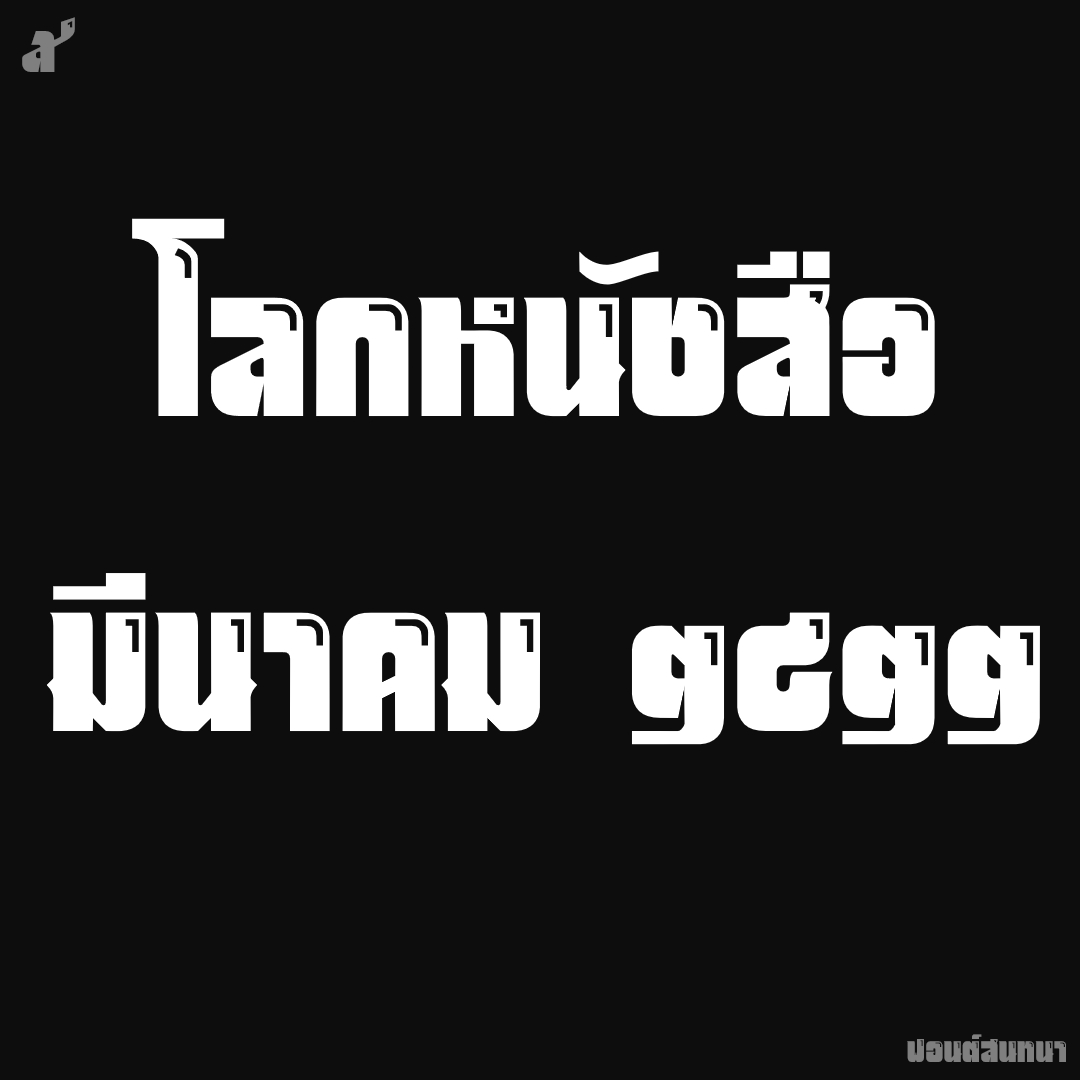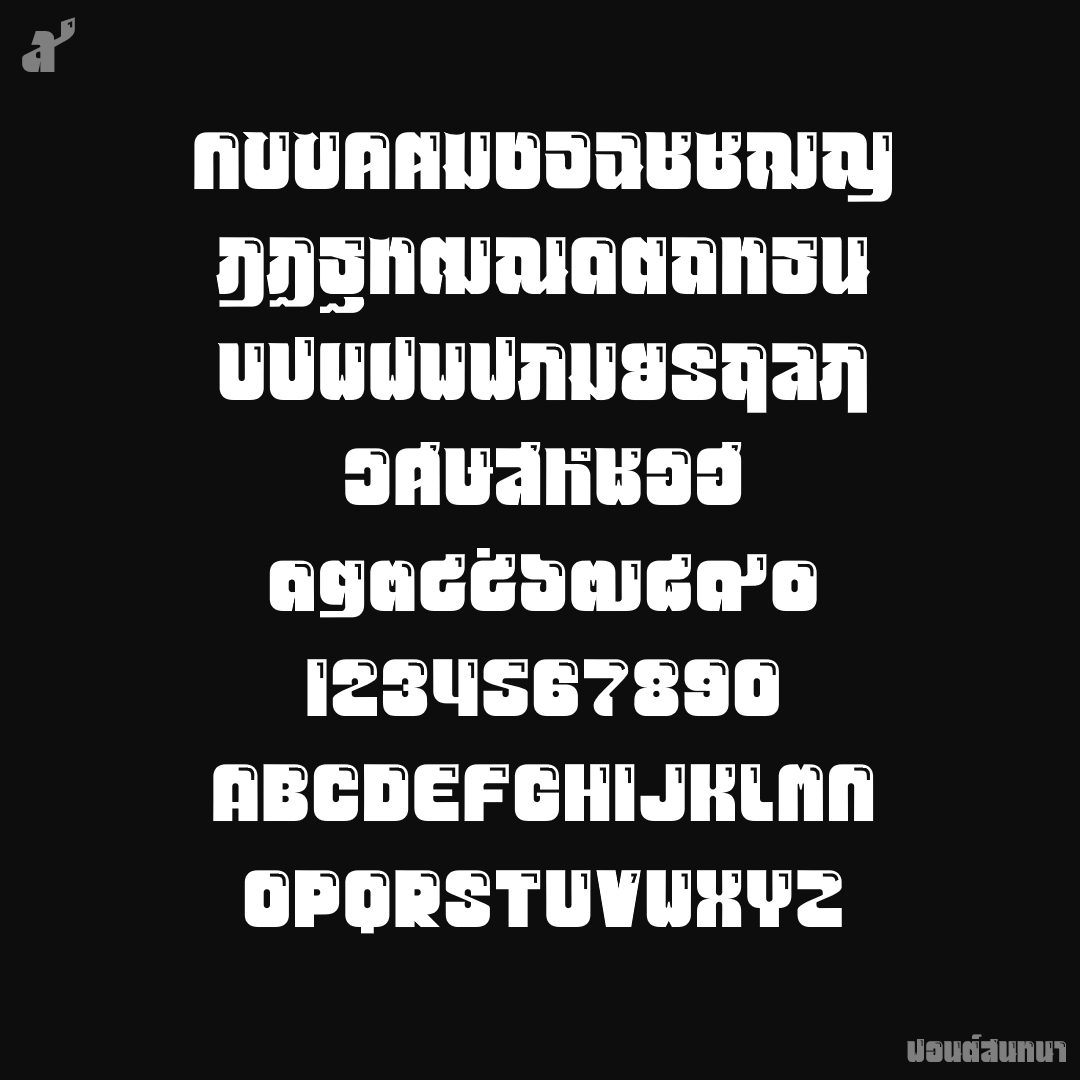
ฟอนต์ สนทนา
ต้นทางจากโลกหนังสือ ฉบับ มีนาคม ๒๕๒๒ อักษรไม่มีหัวเมื่อเกือบ 50 ปีที่แล้ว ฟอนต์ดูแข็งแรงแม้จะมีมุมโค้ง..เลยแอบเติมจุดตรงมุมให้ดูป่องขึ้น
ชื่อฟอนต์ : สนทนา
ต้นทางจากโลกหนังสือ ฉบับ มีนาคม ๒๕๒๒ อักษรไม่มีหัวเมื่อเกือบ 50 ปีที่แล้ว ฟอนต์ดูแข็งแรงแม้จะมีมุมโค้ง..เลยแอบเติมจุดตรงมุมให้ดูป่องขึ้น